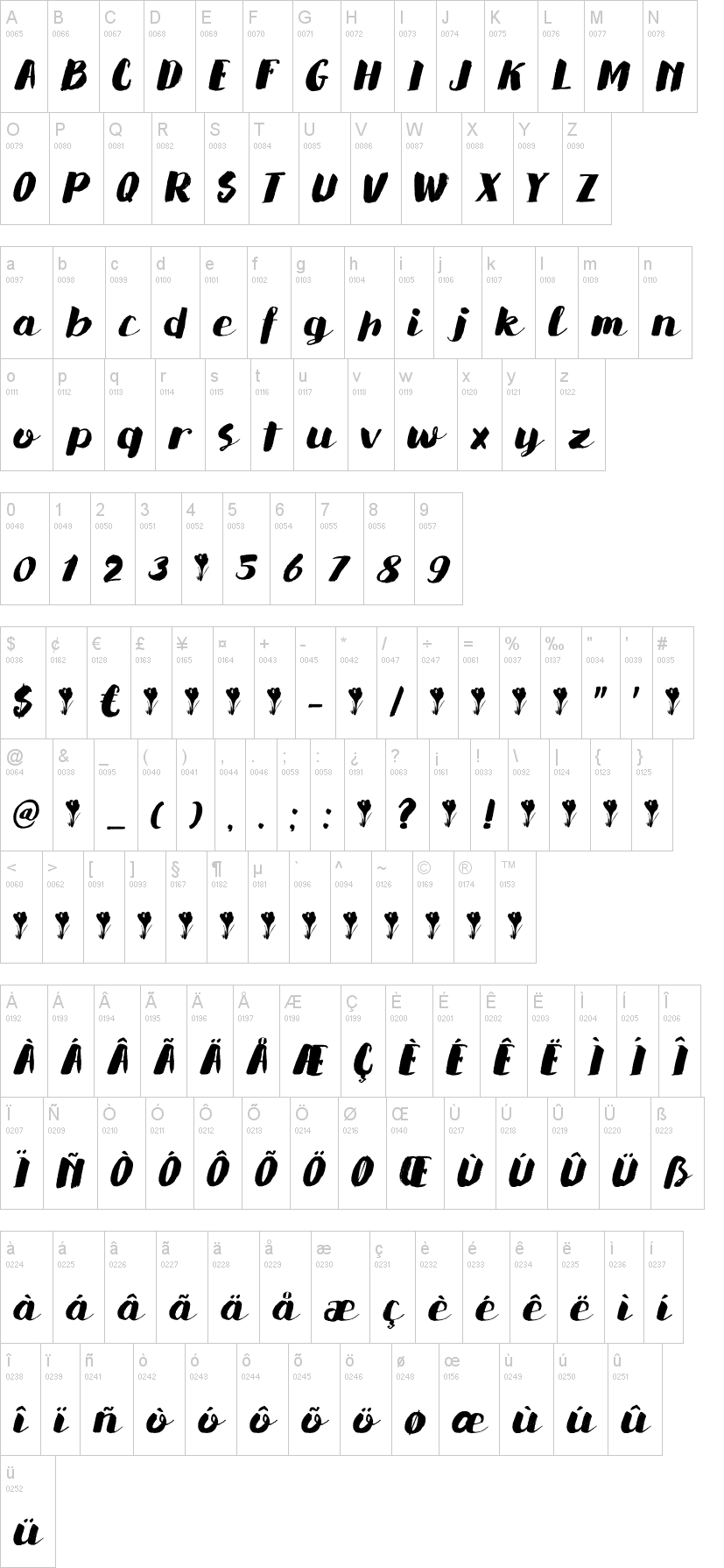
? DK Saffron Walden 是一款由 David Kerkhoff 创作的精美字体,它有着温暖而优雅的设计,能够提供给您更多的设计灵活性。DK Saffron Walden 字体的特点是它的优雅,它的字体设计让您的文字充满活力,而且它的字形精致,能够让您的文字更加精美可观。它还有着宽松的节奏,可以让您的文字更加流畅。DK Saffron Walden 字体适用于任何类型的平面设计,可以让您的作品更加精致而又细腻。内容介绍
DK Saffron Walden是一款非常不错的手写艺术字体,具有很好的视觉感,适合于文化类的宣传设计、商业类品牌的广告和产品包装设计以及个性化文字排版等较多场景。